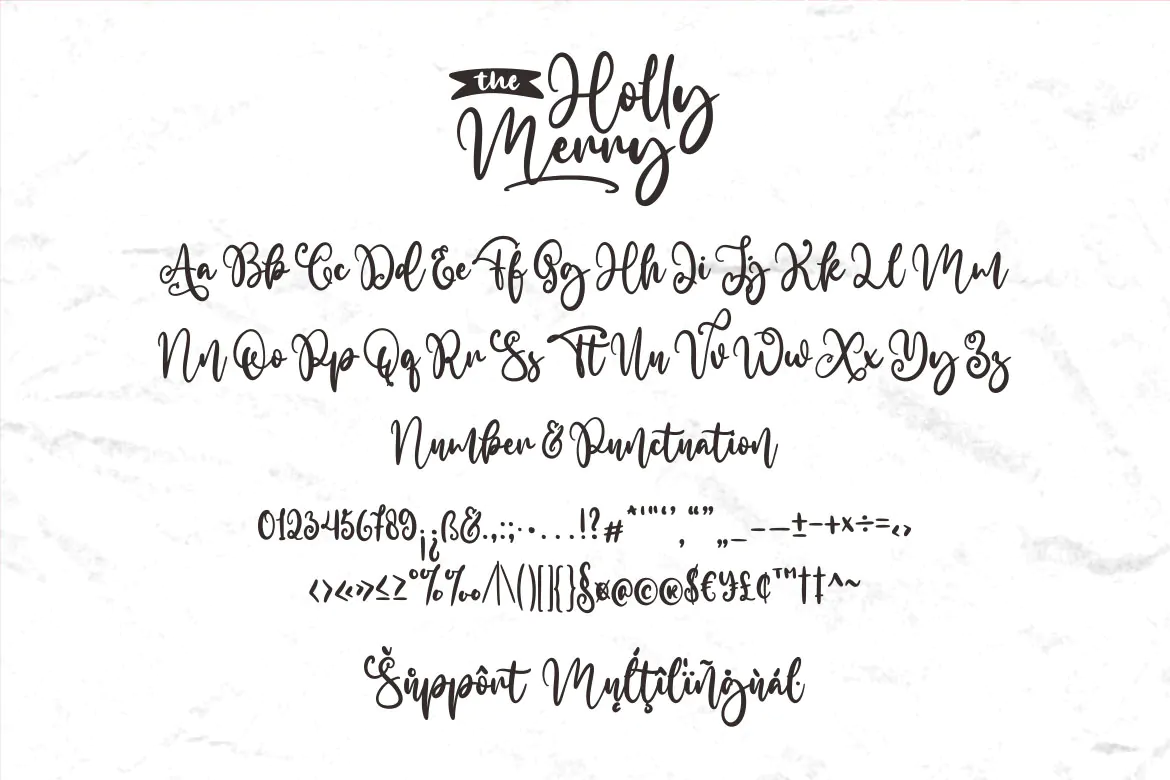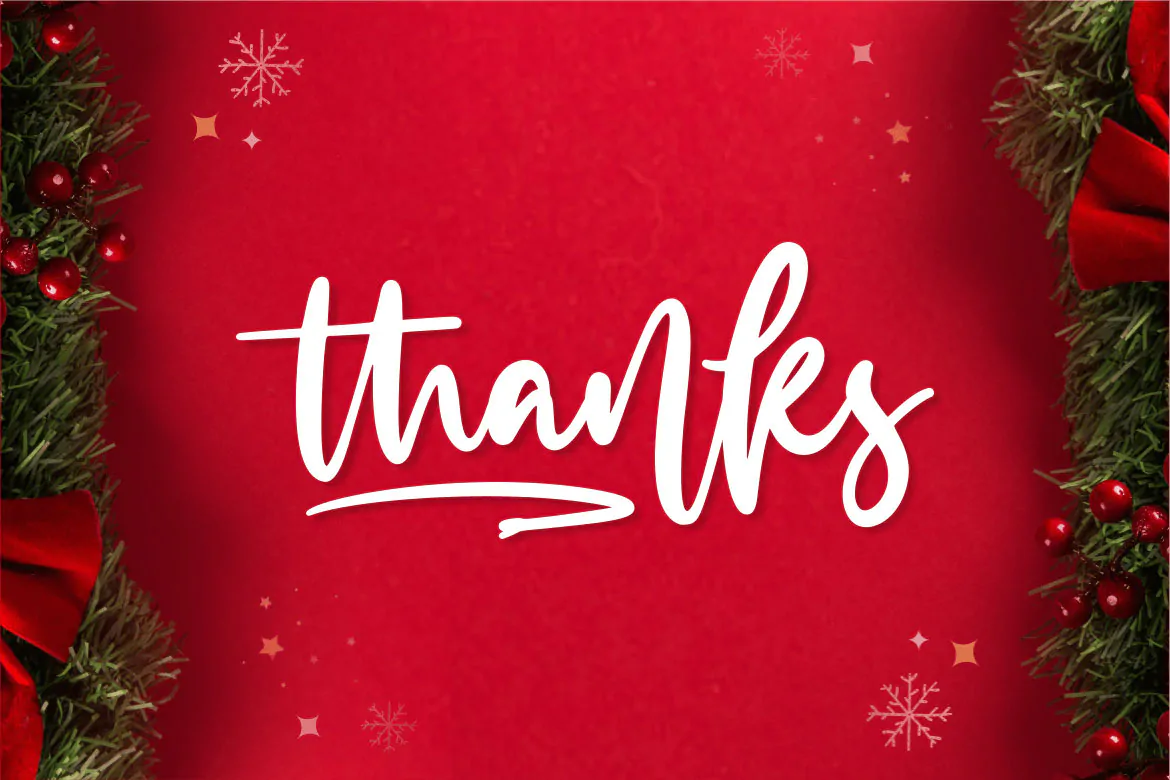
فونت کریسمس The Holly Merry
فونت کریسمس دستنویس
فونت کریسمس The Holly Merry یک قلم دستنویس زیبا است که به سبک پیوسته نویسی طراحی شده است و مناسب برای طراحی انواع کارت و پوستر میباشد.